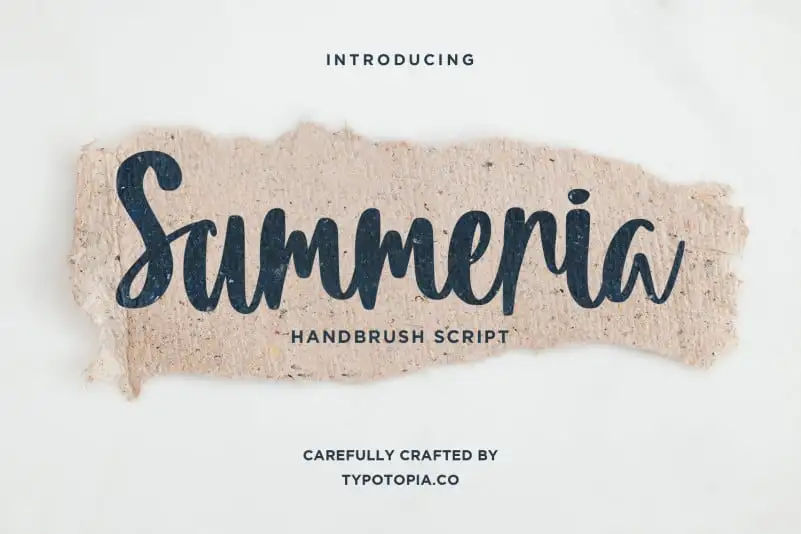
Summeria Handbrush Script Font – Download Grátis
A Summeria Handbrush Script Font é uma elegante fonte de calligrafia moderna com um toque casual que oferece aos designers incríveis opções para seus próximos projetos criativos. É perfeita tanto para criar logotipos, cartões, convites e embalagens de produtos, como também para adicionar uma personalidade única a cabeçalhos, logotípios, assinaturas ou até mesmo rótulos para etiquetas. Esta fonte é um presente para todos os designers que desejam dar um toque especial à sua arte digital e física, com uma gama de possibilidades infinitas. Não perca tempo, experimente a Summeria Handbrush Script Font na sua próxima projeto design, ela certamente o impressionará. Com sua tipografia elegante e acessível em estilo casual, esta fonte será um verdadeiro acréscimo a qualquer trabalho de design que você estiver realizando — seja para criar identidades visuais impactantes ou elementos decorativos para produtos em formato físico. Através da Summeria Handbrush Script Font, seus designs ganham vida e ficam ainda mais únicos. Experimente-a agora e faça seu próximo projeto brilhar!